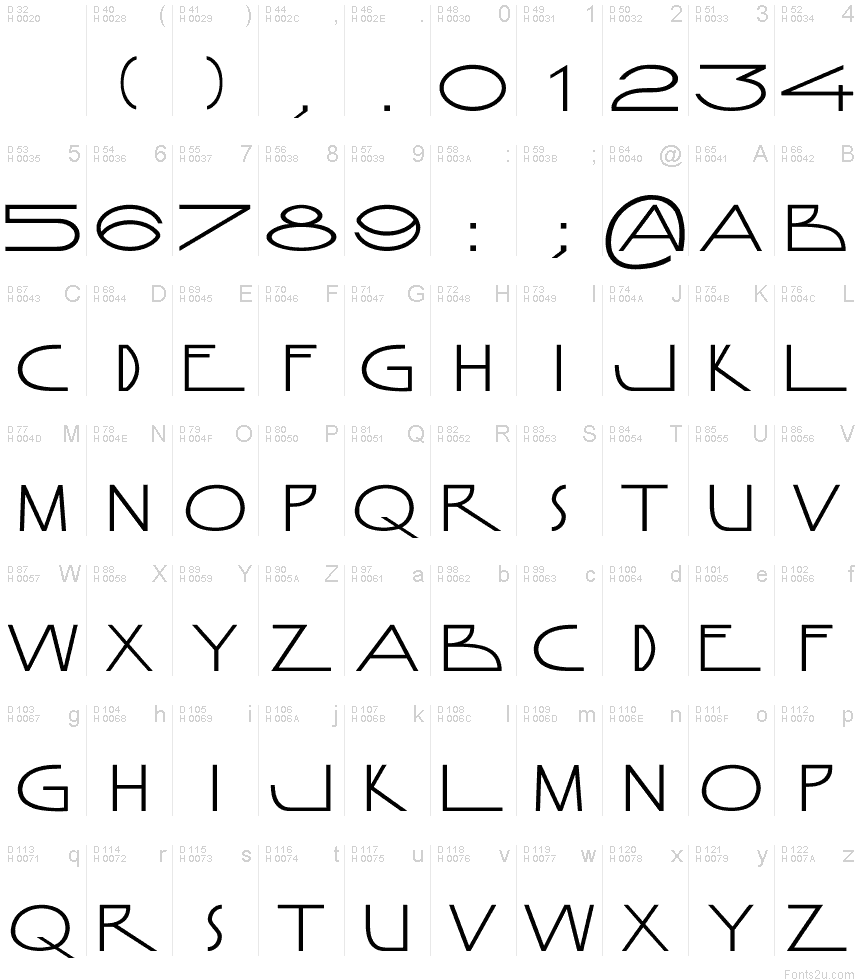
Anamorphosée Normal
Com N'B 1995 & Keyan juillet 1999.
Com N'B, retranscrit et modifié par Keyan
Police utilisée par Com N'B pour écrire le nom de Mylène Farmer sur l'album anamorphosée. Recréée, modifiée et complétée par Keyan.